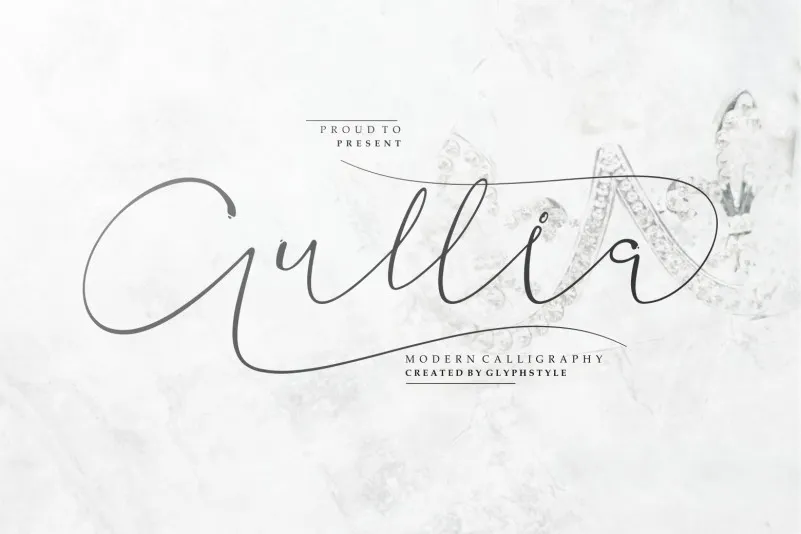
Aullia Modern Calligraphy Font – Download Grátis
Aullia Modern Calligraphy Font é uma fonte moderna do gênero calligrafia, conhecida por seu aspecto elegante e luxuoso. Suas letras apresentam um charme sofisticado que as torna perfeitas para diversos aplicativos, desde criação de logos e cartões de visita até designs de mídia social e embalagens de produtos. Aullia é uma escolha ideal para quem busca transpor seu estilo elegante em qualquer projeto que exija a presença de um rótulo de calligrafia moderna. Seja para eventos, como casamentos ou festas infantis, ou simplesmente para personalizar suas mensagens digitais e impressas, Aullia Modern Calligraphy Font é uma opção que se adequará perfeitamente ao seu projeto. É a fonte certa para quem valoriza tanto estilo quanto funcionalidade em sua marca.